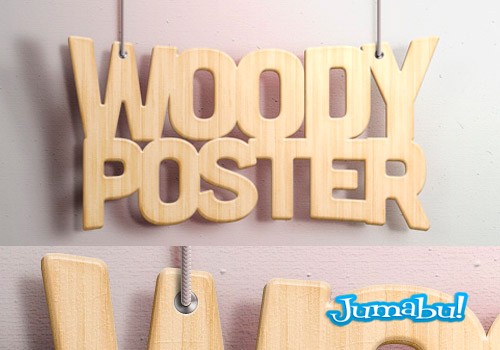
Efecto Madera con Photoshop! Podrán descargar un hermoso PSD con las capas correspondientes para que puedan ver como se realiza un efecto madera generado por estilos en photoshop.
Simple, bonito y super páctico!
Espero que estas tipografias con efectos madera les encanten como a mi!